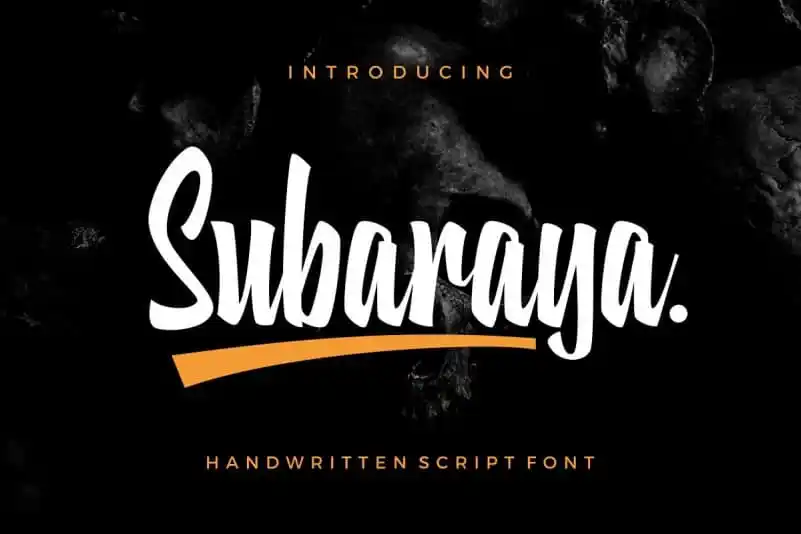
Subaraya Script Font – Download Grátis
A Subaraya Script Font é uma elegante escolha para aqueles que desejam adicionar um toque único às suas criações digitais. Com mais de cem novos símbolos e várias alternativas, ligaturas numerárias e recursos OpenType avançados para frações, essa fonte oferece um estilo de script manuscrito que adiciona um toque masculino perfeito a design gráfico como logotipos, headlines e designs impressos em camisetas. Ela é o ideal para quem busca uma fonte moderna e sofisticada capaz de transformar qualquer projeto em algo realmente especial. Com a Subaraya Script Font, as possibilidades são quase infinitas.